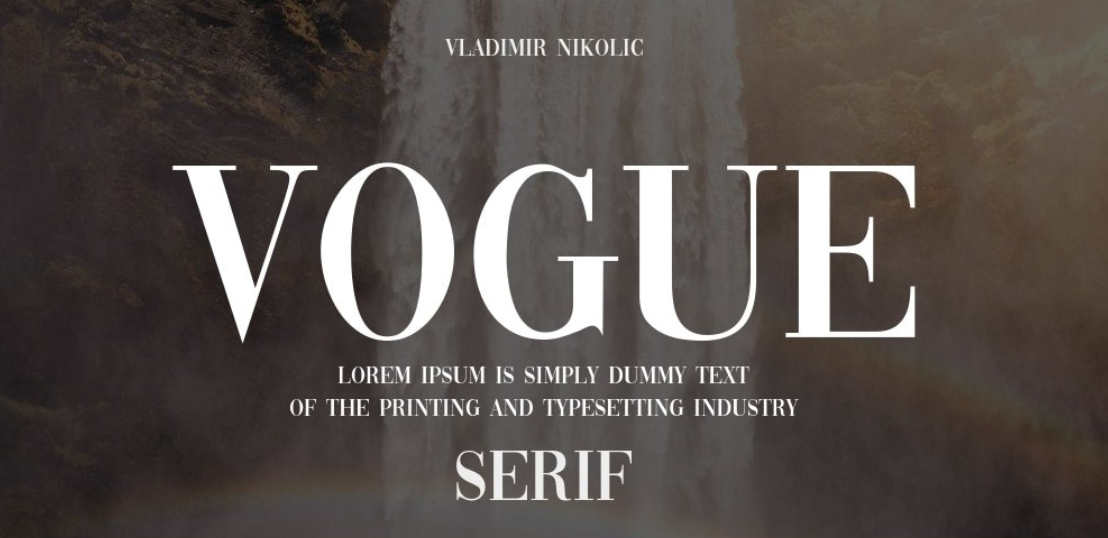
Vogue Free Font là từ khóa được giới designer săn lùng hàng đầu khi cần tái tạo lại phong cách Typography biểu tượng của tạp chí thời trang danh tiếng nhất thế giới. Thực chất, phần chữ “VOGUE” trên bìa tạp chí sử dụng một biến thể tùy chỉnh của dòng phông chữ Didot (Modern Serif) với độ tương phản nét thanh đậm tột đỉnh và các chân chữ sắc lẹm. Bên cạnh việc tìm kiếm tệp phông chữ cài đặt, nhiều người cũng tìm kiếm Vogue Font PNG (dạng ảnh tách nền) để chèn nhanh vào các bản thiết kế số. Doozypack.vn cung cấp link tải trọn bộ phông chữ phong cách Vogue chuẩn kỹ thuật, hỗ trợ đầy đủ tiếng Việt giúp bạn tự tin thiết kế bao bì thời trang và mỹ phẩm xa xỉ.
Sức hút từ phong cách Typography của tạp chí Vogue
Không một tín đồ thời trang nào không nhận ra dòng chữ “VOGUE” với cấu trúc kéo dài, thanh lịch và quyền lực. Việc ứng dụng phong cách này vào bao bì sản phẩm mang lại giá trị nhận diện vượt trội.
Biểu tượng thời trang cao cấp mang âm hưởng Modern Serif
Đặc trưng lớn nhất của phong cách phông chữ Vogue là sự đối lập mãnh liệt giữa các nét dọc dày dặn và các nét ngang mỏng như sợi tơ (hairline). Tỷ lệ chữ được kéo dãn theo chiều dọc, tạo nên một diện mạo vô cùng kiêu kỳ, sắc sảo và mang đậm tinh thần Haute Couture. Khi đặt tiêu đề theo phong cách này lên bao bì, sản phẩm của bạn sẽ ngay lập tức toát lên vẻ đắt tiền, quý phái và chuẩn mực quốc tế.
Sự khác biệt giữa việc dùng Vogue Font dưới dạng Vector và PNG
Nhiều người thường tìm kiếm Vogue Font PNG để chèn nhanh vào banner hoặc video ngắn. Tuy nhiên, các tệp ảnh PNG thường bị giới hạn độ phân giải (pixel) và không thể thay đổi nội dung chữ. Đối với các ấn phẩm sản xuất bao bì thực tế (như in Offset hộp giấy hay túi giấy), việc sử dụng phông chữ dạng Vector (OpenType/TrueType) cài đặt trực tiếp là bắt buộc để đảm bảo độ sắc nét tuyệt đối, không bị vỡ hình khi phóng to.
Ưu điểm nổi bật của các bản font phong cách Vogue Việt hóa
Khi ứng dụng các phông chữ thời trang quốc tế vào thị trường trong nước, sự chỉn chu về dấu câu là yếu tố quyết định đến tính chuyên nghiệp của bản thiết kế:
- Khắc phục triệt để lỗi dấu tiếng Việt: Các bộ phông chữ Didot chuẩn Việt hóa tại Doozypack.vn đã được trau chuốt thủ công từng dấu câu. Các dấu sắc, huyền, hỏi, ngã, nặng được vẽ thanh mảnh đồng nhất cùng thân chữ gốc, không gây cảm giác chắp vá hay làm đè nét làm mất tính thẩm mỹ hoàng gia.
03 Ứng dụng thực tế của phông chữ Vogue trong sản xuất bao bì tại Doozypack.vn
Sự kiêu sa và thanh lịch của phong cách Vogue mang lại hiệu ứng thị giác đắt giá trên các dòng sản phẩm bao bì thực tế do Doozypack.vn sản xuất:
- Hộp giấy đựng Nước hoa & Mỹ phẩm Luxury: Tiêu đề thương hiệu in bằng phông chữ phong cách Vogue kết hợp kỹ thuật ép kim nhũ vàng trên giấy Ivory cán màng mờ tạo nên vẻ đẹp sang trọng chuẩn phong cách thời trang Paris.
- Túi giấy thời trang cao cấp: Tên cửa hàng in bằng phông chữ phong cách Vogue màu đen tối giản trên nền túi giấy trắng giúp khẳng định gu thẩm mỹ tinh tế của nhãn hàng trong mắt người tiêu dùng.
- Nhãn dán chai Rượu vang & Nến thơm: Nét chữ Serif sắc sảo mang lại cảm giác thư giãn, sạch sẽ và thượng lưu cho các dòng sản phẩm quà tặng tinh tế.
Lưu ý kỹ thuật khi in ấn với phông chữ thanh mảnh phong cách Vogue
Việc sản xuất bao bì thực tế sử dụng các phông chữ có độ tương phản cao đòi hỏi sự am hiểu kỹ thuật chuyên sâu tại xưởng in Doozypack.vn:
- Kiểm soát độ dày nét Hairline khi ép kim: Các nét ngang và chân chữ của font khá mảnh. Khi gia công ép kim vàng (Hot Stamping), designer nên đảm bảo nét chữ có độ dày tối thiểu 0.15mm để nhũ bám dính sắc nét, không bị đứt đoạn.
- Chọn chất liệu giấy phẳng mịn: Phông chữ này đẹp nhất khi in trên giấy Ivory, Couche hoặc giấy mỹ thuật nhẵn. Tránh in các nét chữ quá thanh trên bề mặt giấy Kraft thô nhám vì mực dễ bị loang làm mất đi độ sắc sảo của nét chữ.